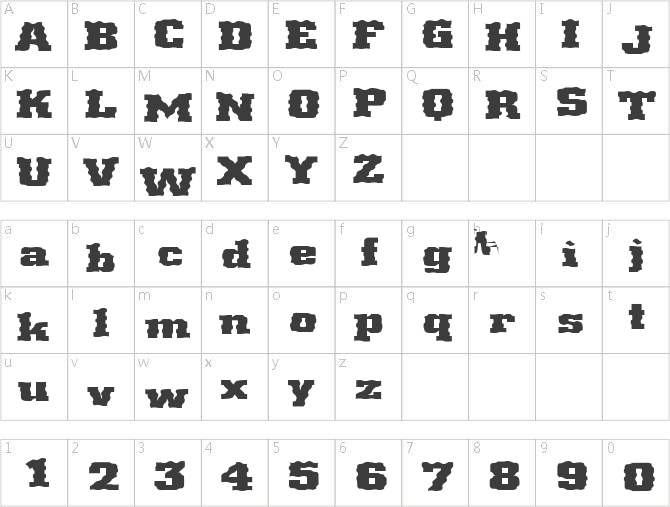
FZ BASIC 53 WAVEY EX 詳情頁(yè)
FZ BASIC 53 WAVEY EX字體字庫(kù)是一款讓人賞心悅目、百看不厭的英文字體,適合各類(lèi)廣告和產(chǎn)品包裝設(shè)計(jì)應(yīng)用,字體大小0.13MB,格式為ttf字體,上傳用戶(hù)是wo~,作者/版權(quán)方為未知